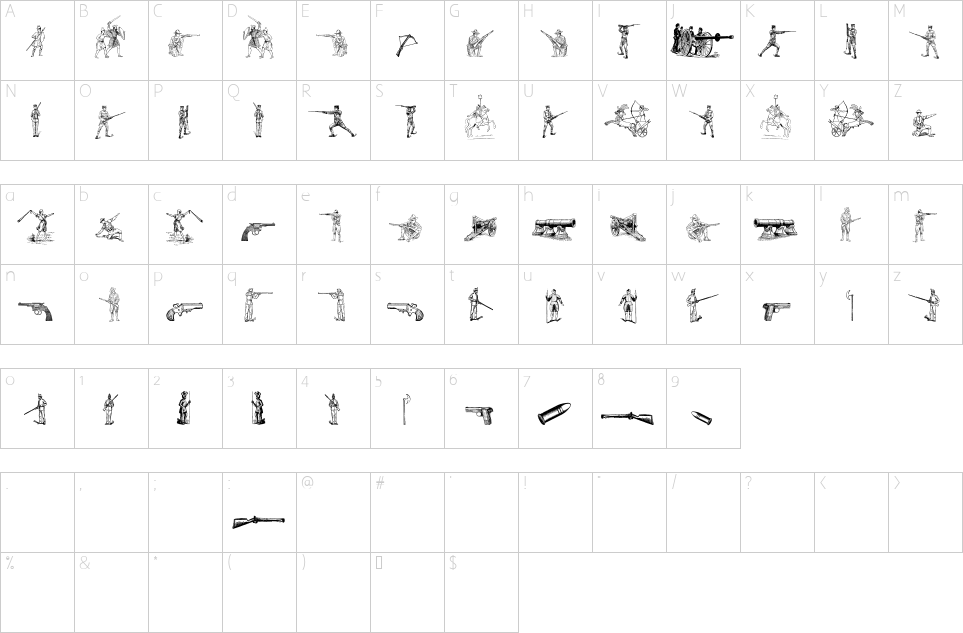
Fontes gratuitas são sempre uma excelente maneira para designers aprimorarem suas habilidades sem gastar muito dinheiro. Recentemente, foi lançada Das Krieg Font, uma opção moderna e poderosa para quem busca personalidade e estilo único em seus projetos digitais. Esta fonte foi criada pela Intellecta Design e tem sido baixada mais de 9,837 vezes. Das Krieg é a escolha perfeita para criar títulos impactantes ou detalhes finos em qualquer projeto de design gráfico. Se você está procurando por uma fonte de qualidade sem ter que pagar grandes sumas, Das Krieg é um excelente lugar para começar. Combinada com o design poderoso da Intellecta Design, esta font oferece a oportunidade de dar vida à sua arte digital. Não perca tempo e descubra por si mesmo como Das Krieg pode tornar seus projetos mais impressionantes.